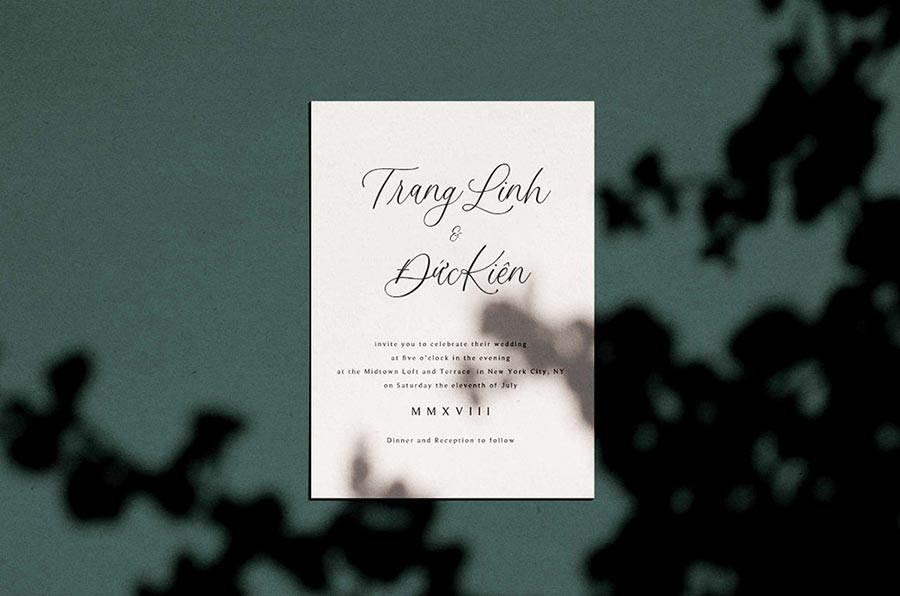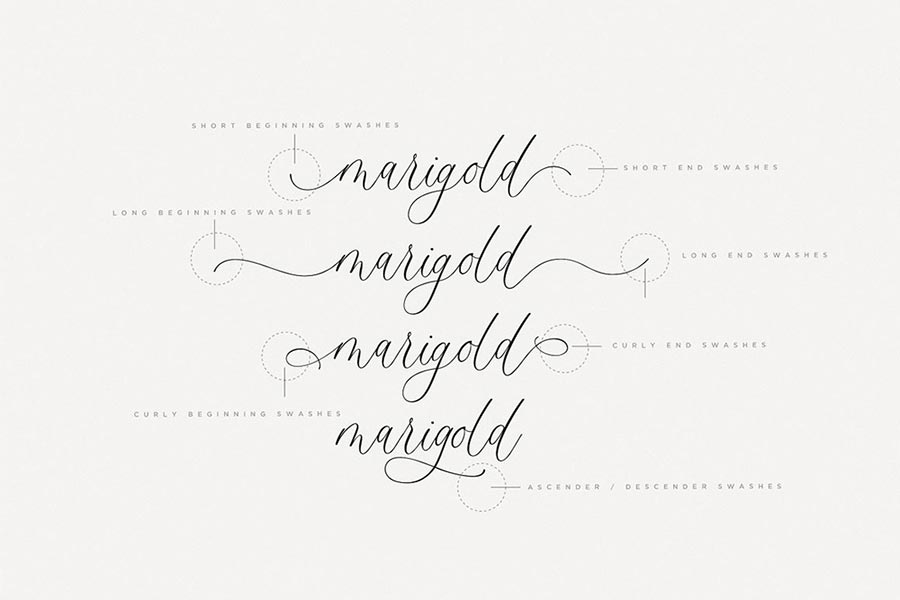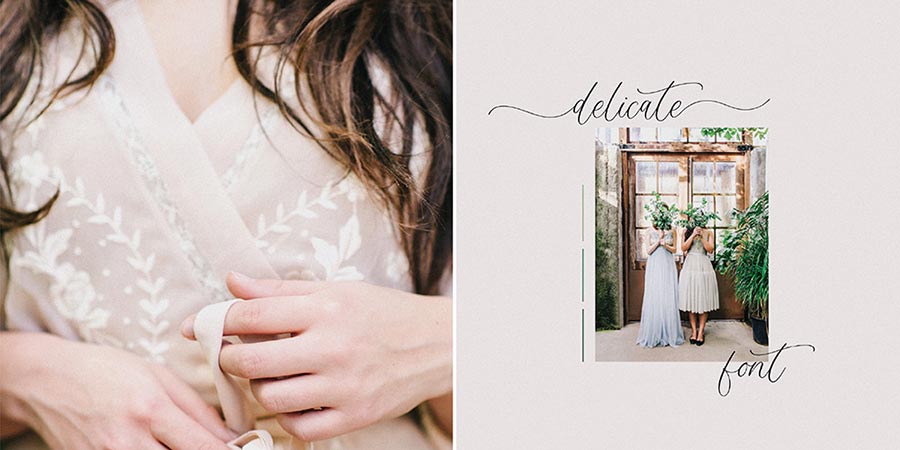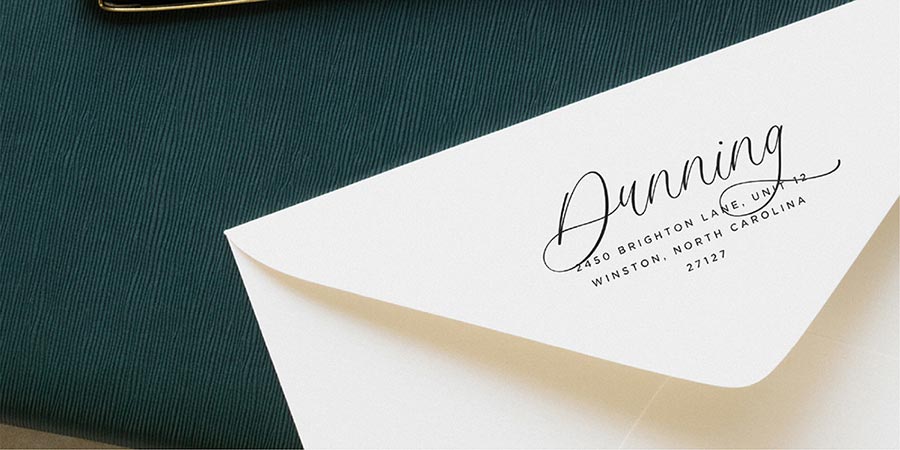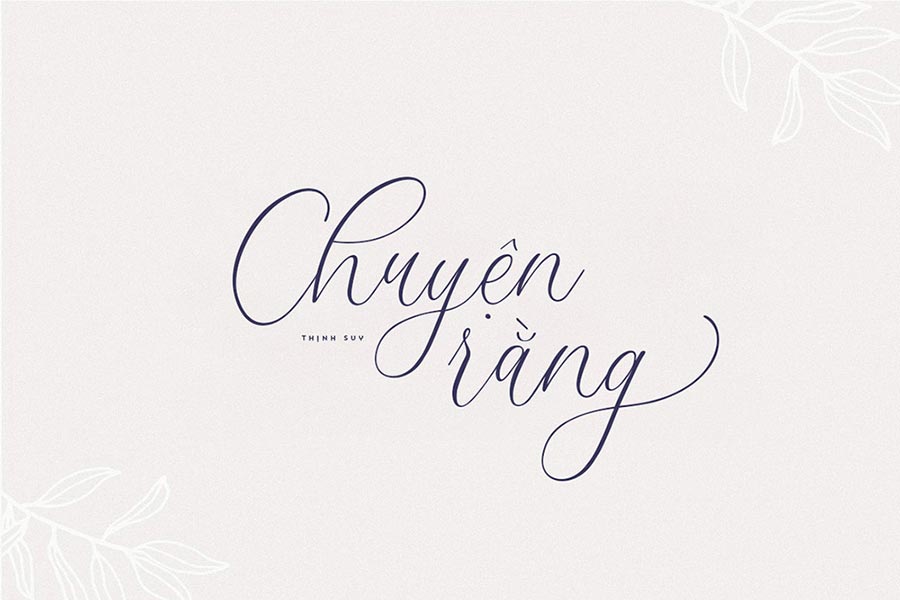
Chia Sẻ Miễn Phí Font Việt Hóa - Montery Script Chữ Viết Tay Mỏng Và Nhẹ Nhàng
Font chữ không chỉ là công cụ thể hiện nội dung mà còn là yếu tố quan trọng giúp tạo nên phong cách và cảm xúc cho thiết kế. Sadesign.vn tự hào giới thiệu và chia sẻ miễn phí font Việt hóa Montery Script – một sự lựa chọn hoàn hảo cho những ai yêu thích sự thanh thoát, nhẹ nhàng và tinh tế trong từng nét chữ.
Montery Script là một font chữ viết tay mang phong cách hiện đại, được thiết kế với các đường nét mỏng, mềm mại và uyển chuyển. Font này đặc biệt phù hợp cho các dự án thiết kế cần sự lãng mạn, nhẹ nhàng hoặc mang hơi hướng cá nhân hóa. Với sự hỗ trợ đầy đủ tiếng Việt, Montery Script đã được Việt hóa để đáp ứng nhu cầu sử dụng của người dùng trong nước.
Điểm nổi bật của Montery Script nằm ở sự cân bằng hoàn hảo giữa tính thẩm mỹ và tính ứng dụng. Các đường nét mảnh mai nhưng không kém phần chắc chắn, giúp font này dễ dàng kết hợp với nhiều phong cách thiết kế khác nhau, từ thiệp mời, logo, đến các bài đăng trên mạng xã hội.
Font Montery Script Việt hóa không chỉ là một công cụ hỗ trợ thiết kế mà còn là nguồn cảm hứng sáng tạo cho những ai yêu thích sự tinh tế và mềm mại trong từng đường nét chữ. Với sự chia sẻ miễn phí từ Sadesign.vn, bạn không chỉ tiết kiệm chi phí mà còn có cơ hội trải nghiệm một trong những font chữ viết tay đẹp nhất hiện nay.